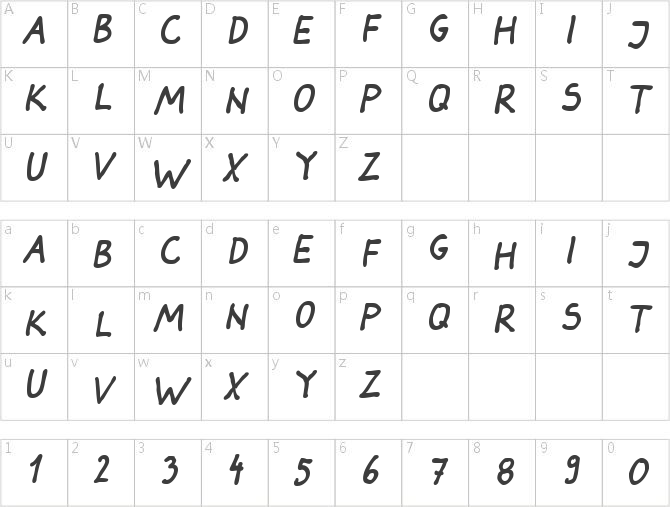
字體名稱: Darbog
Darbog bold italic
Darbog bold italic介紹
Darbog bold italic字體字庫是一款讓人賞心悅目、百看不厭的英文字體,適合各類廣告和產(chǎn)品包裝設(shè)計應用,字體大小0.08MB,格式為ttf字體,上傳用戶是@小咖,作者/版權(quán)方為未知